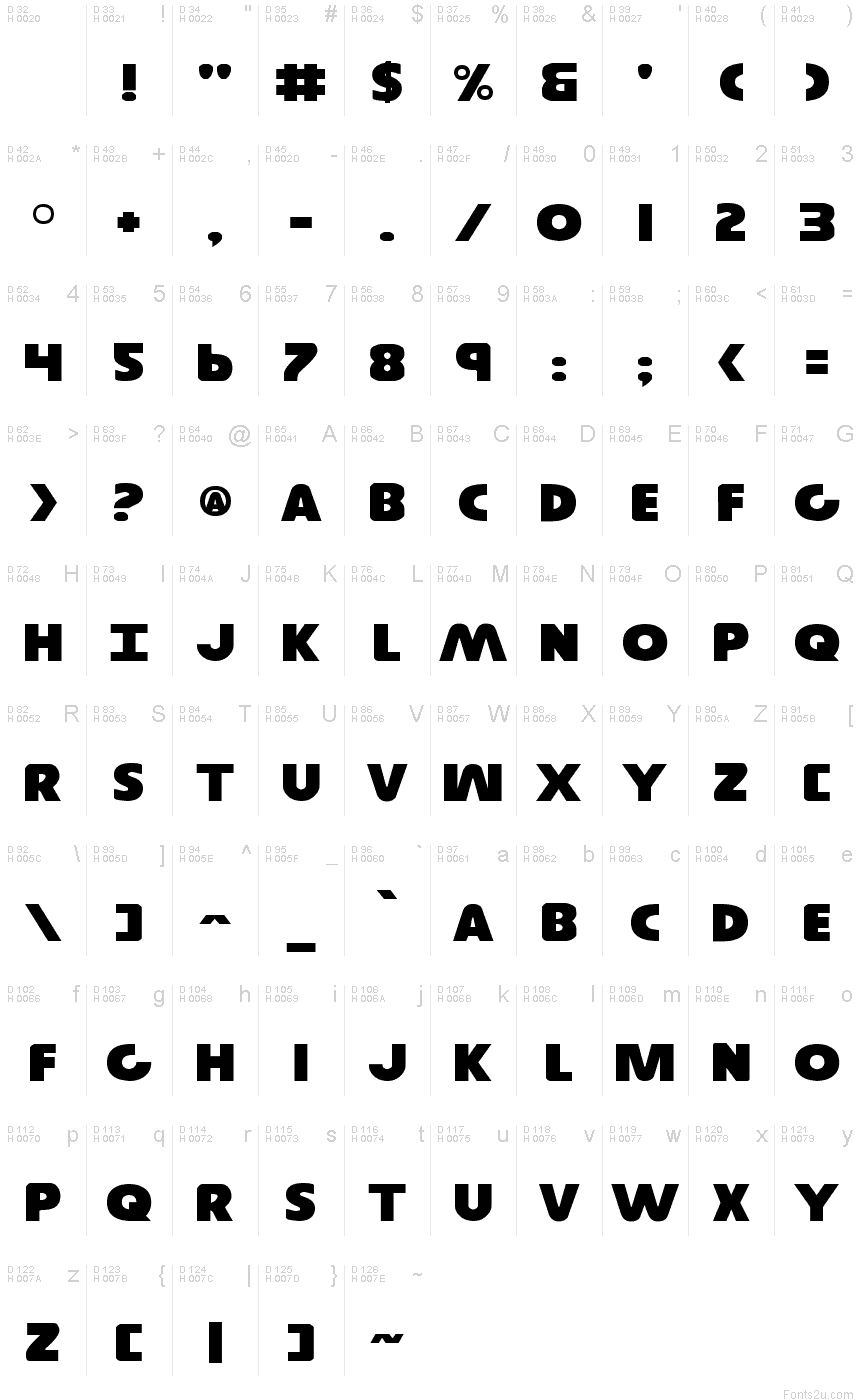
Governor Expanded von Iconian Fonts ist eine moderne, kostenlose Display-Schrift. Mit ihrem extra breiten Stand, den kräftigen Strichen und abgerundeten Ecken wirkt sie wie ein starker Stempelabdruck – markant, aber niemals aggressiv. Die Buchstaben stehen eng und kompakt zusammen und bilden massive, dunkle Textblöcke, die selbst aus der Ferne sofort ins Auge fallen, wie eine Stadiongrafik oder ein großflächiger Wandaufdruck.
Mit Governor Expanded gelingen dir aufmerksamkeitsstarke Titel für Sportgrafiken, Spiele-Cover, Filmplakate, Album-Artworks, Verpackungen oder ausdrucksstarke Web-Banner. Diese kostenlose Schrift glänzt besonders, wenn sie groß und eng gesetzt wird. Kombiniere sie einfach mit einer klaren, schmaleren serifenlosen Schrift für begleitende Texte, um die breite, muskulöse Form von Governor Expanded perfekt auszubalancieren.